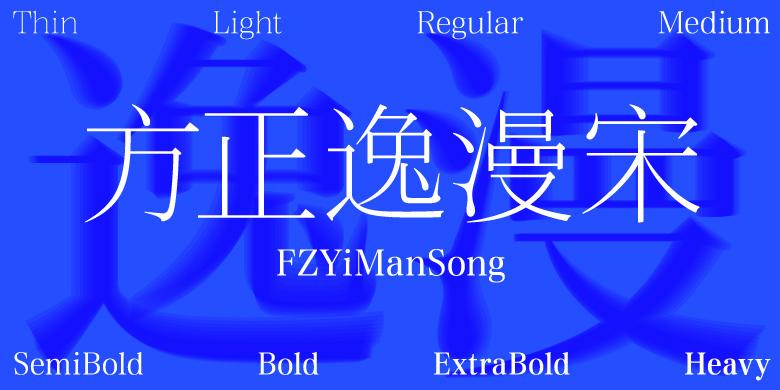
方正逸漫宋家族
方正逸漫宋家族,这款字体结构工整、笔画清晰,兼顾美观与易读性,适用于标题、正文、海报、包装、LOGO 等多种场景。字形优雅稳定,风格百搭耐看,适配日常排版与创意设计,让文字呈现更舒适、更具质感。方正逸漫宋家族一笔一画,皆是细节,以均衡的比例、流畅的线条打造舒适视觉体验,字形端正大气,风格简约现代。无论是商业设计、品牌宣传还是日常排版,都能轻松驾驭,让文字更有格调与力量。方正逸漫宋家族字体下载。
字体品牌: 方正字库 设计师:郭炳权,杨悸 字体分类:宋体 字体属性:精品字 字符集:大陆简体(GB2312-80) 发布时间: 2024
“逸漫宋”起笔缓慢,收笔柔和,点如水滴圆润,犹如女人婀娜多姿又体态丰腴的身材,一撇一捺干净利落,风格简约,每个笔画进行着有序的排列,用右边部件承包左边部件,拥有特式和大胆创新感受,在视觉上充满特色美感,适合男女高档品牌的宣传和包装,是最佳商业百搭字体。